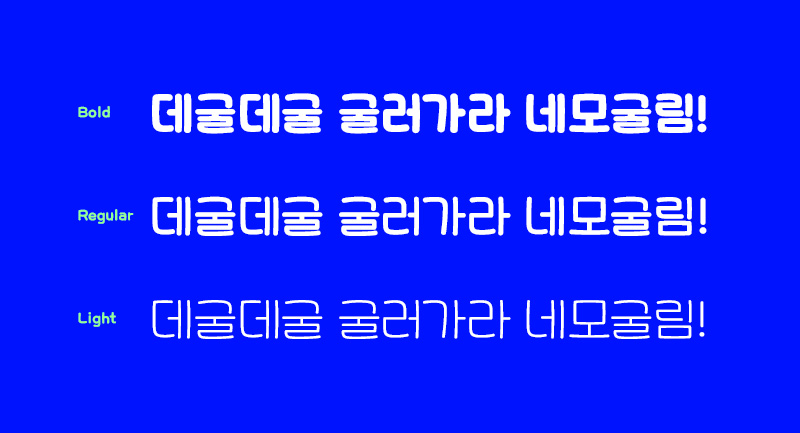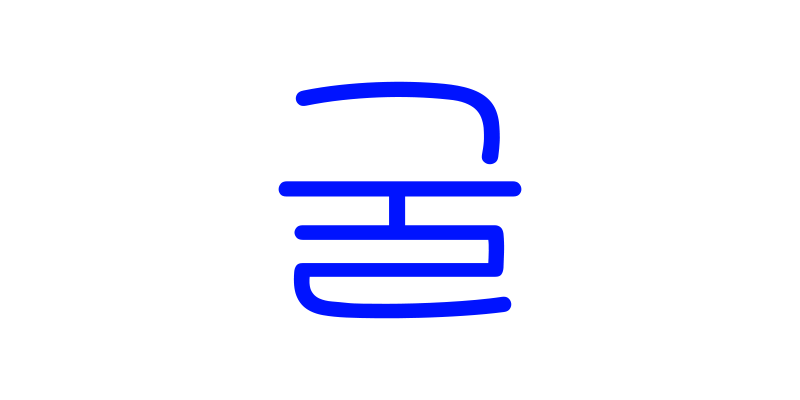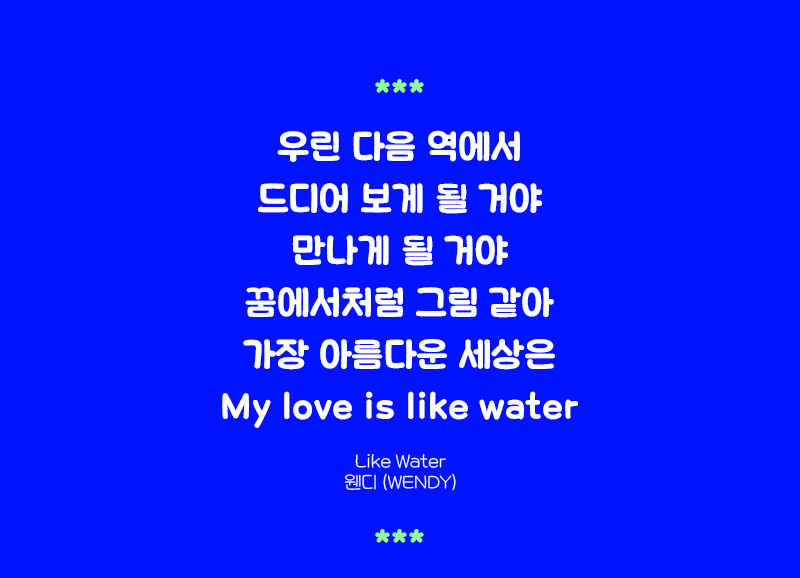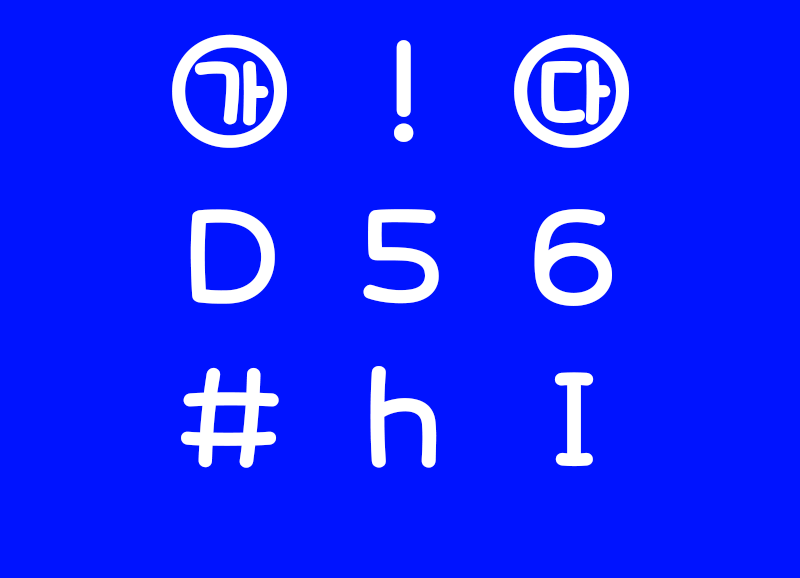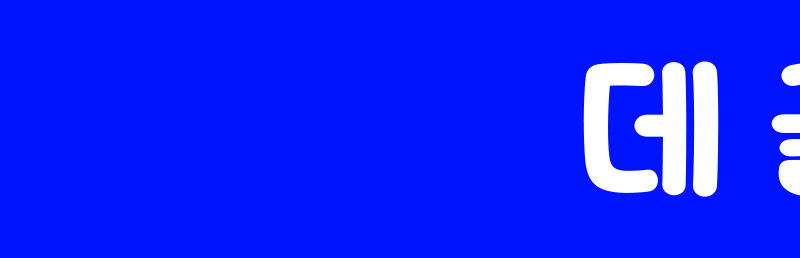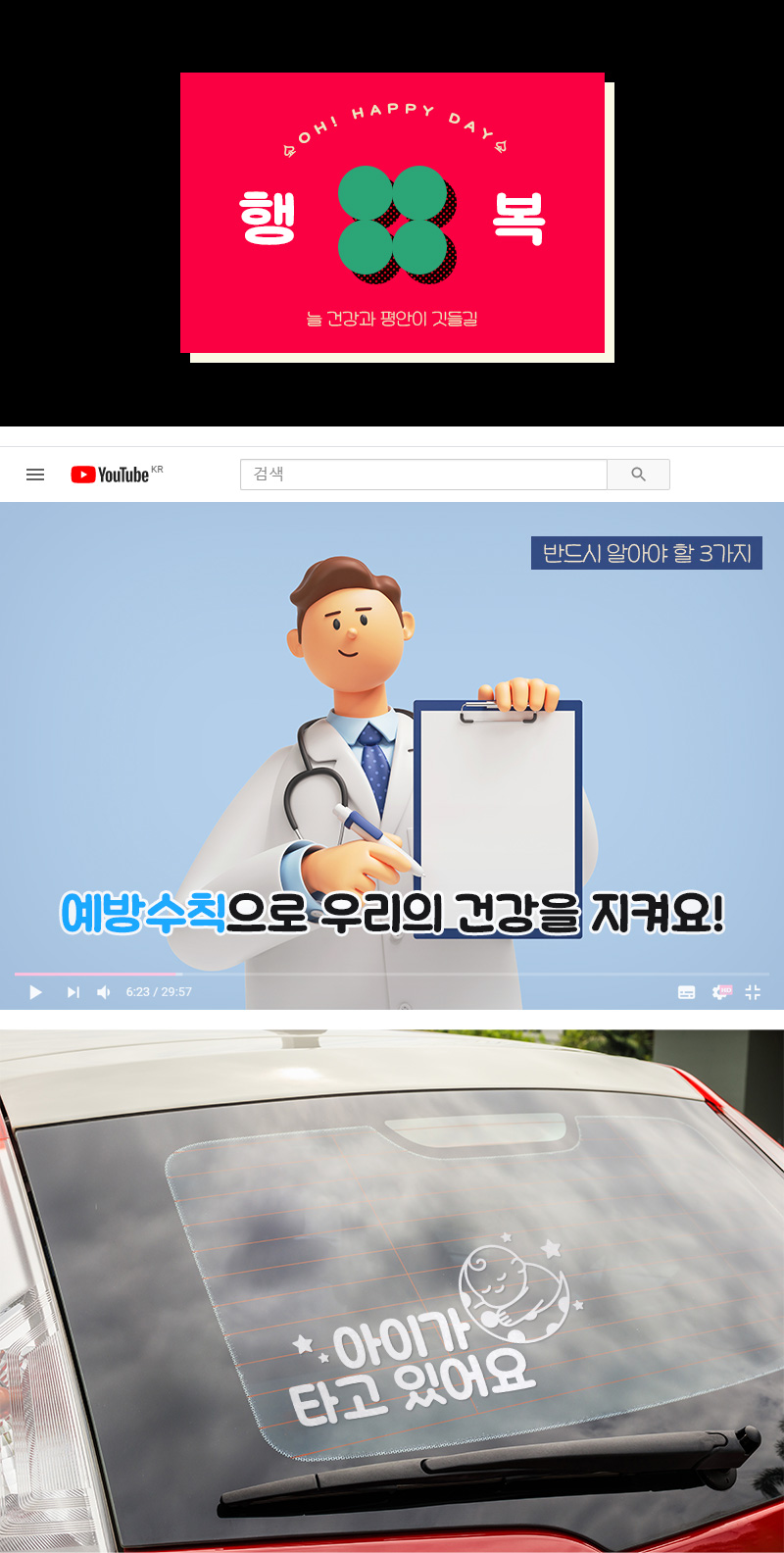
RixRollingSquare
3 Style - Bold, Regular, Light네모난 골격에 각이 진 부분을 둥글게 만들어 데굴데굴 굴러가는 모습을 연상시키는 귀여운 서체입니다.
중심 쪽의 직선적인 획에서 바깥쪽으로 갈수록 텐션을 넣어 정돈되면서도 친근한 느낌을 주며
여러 웨이트로 제작해 영상 자막, 인쇄물, 배너 등 다양하게 활용하기 좋습니다.
| FontFamily | Rix네모굴림 / RixRollingSquare |
|---|---|
| Design | Park Yong-rak, Lee Su-ha |
| Direction | Park Yong-rak |
| Year | 2022Year |